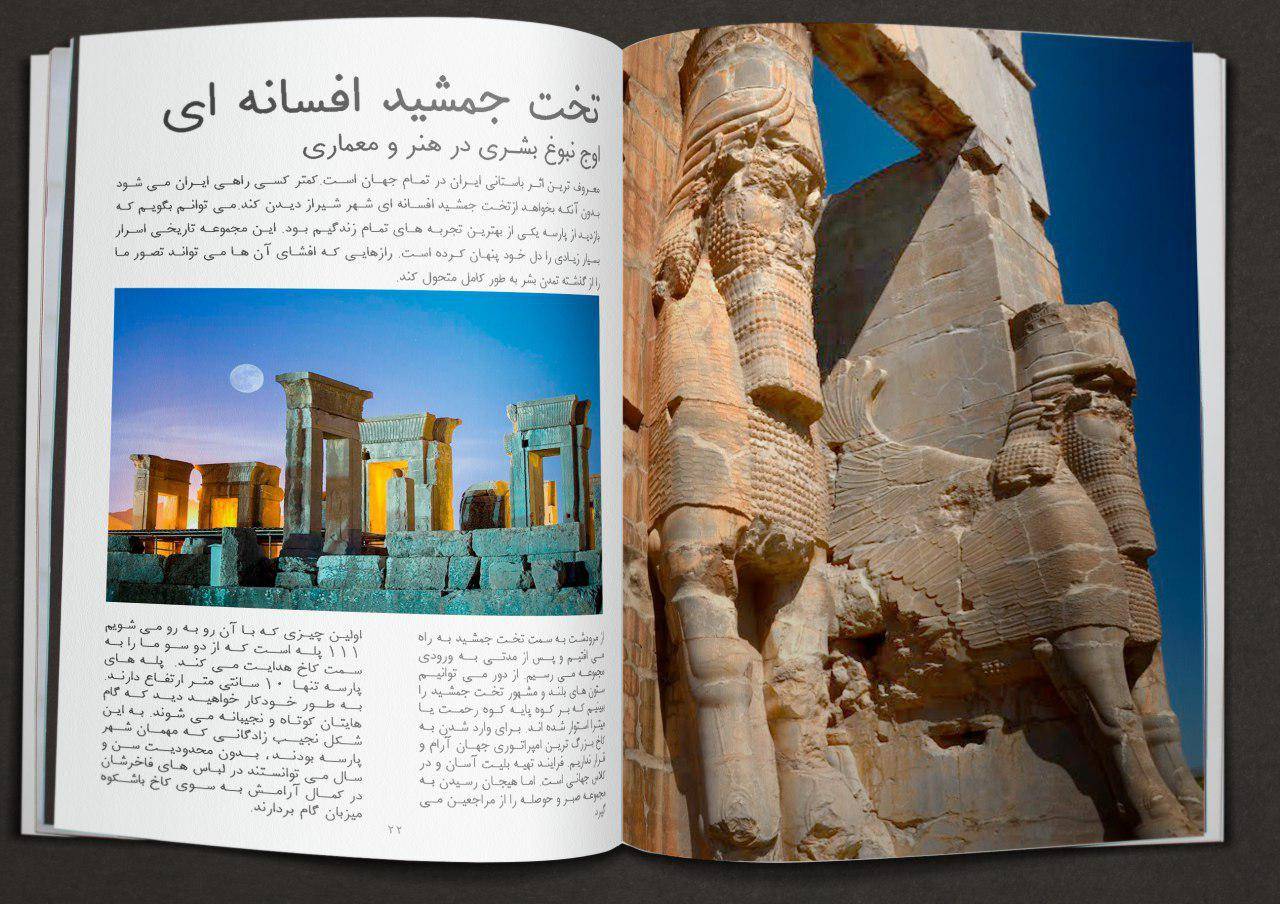
دانلود فونت فارسی ساده | Sadeh Font
فونت فارسی ساده | Sadeh Font  از فونت‌های اتوکد می‌باشد که توسط آقای مهدی صباغی برای ویندوز برگردانده شده است و حروف مناسب لاتین به آن اضافه گردیده است.